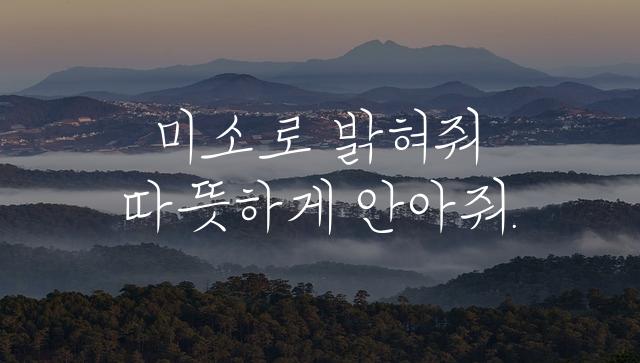
코트라 희망체는 귀여우면서도 또박또박한 둥근 손글씨 스타일의 폰트입니다. 마카의 감성을 담아 따뜻하고 친근한 느낌을 전달합니다.
코트라 희망체은(는)
둥근 스타일, 손글씨, 귀여운 스타일, 펜/붓터치, 감성적인, 부드러움, 복실복실 계열의 생김새를 가지고 있으며
웹/앱 디자인, 보고서/문서, 출판물 제목 등에서 자주 활용되며, 효과적인 메시지 전달에 적합합니다.
이 폰트는 출판/미디어, 기술/IT, 금융/비즈니스 분야에 잘 어울리며,
신뢰감, 명확한, 전문적인 느낌을 담고 있는 것이 특징입니다.